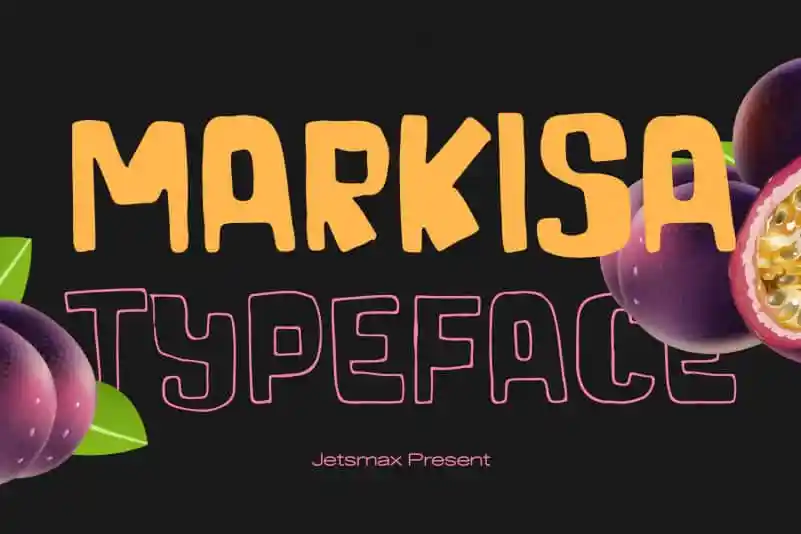
Markisa Display Font – Download Grátis
Markisa Display Font é uma fonte de exibição contemporânea que se baseia fortemente no estilo moderno e à mão livre. O designer jetsmax criou este fonte com duas versões distintas, Regular e Outline, tornando-a perfeita para complementar designs formais e informais. Essa particularidade permite destacá-los ainda mais em qualquer projeto gráfico, seja uma empresa de moda ou um site pessoal, garantindo que seu design seja chamativo e único. A beleza simplificada e a simplicidade de desenho da fonte tornam-se perfeitas para trabalhos que valorizam estética e originalidade.